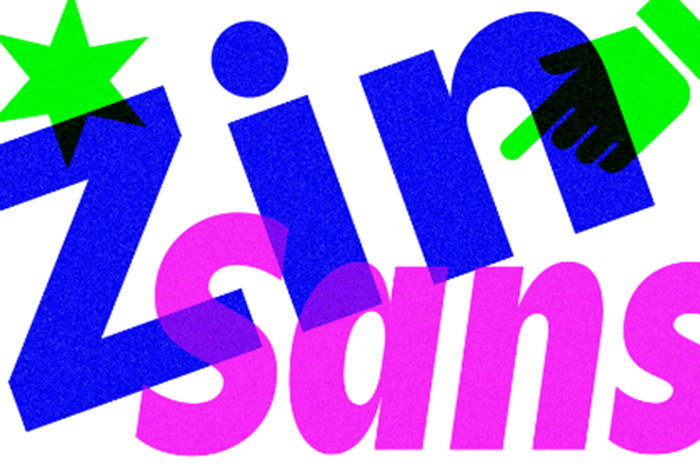
Aproveite uma nova fonte serifless chamada Zin Sans Font Family para suas próximas criações digitais. Introduzida por CarnokyType, a Zin Sans é um tipo de sans-serif projetado para diversas situações na tipografia. Ela destaca-se pela elevada altura do x (x-height), equilibrando uma construção neutra e vertical com formas abertas dinâmicas que têm terminais amplamente abertos. Uma característica notável da fonte é a conexão visual entre os ramos e traços que é mais estreita do que habitualmente encontrada em outros tipos serifless. A Zin Sans vem completa com três proporções de largura (Normal, Condensada e Ampliada), cada uma contendo cinco pesos de tipografia desde o leve até o preto, incluindo itálico correspondente. Todas as fontes incluem minúsculas grandes, caracteres old-style e tabular, ligaturas padrão e alternativas, bem como várias opções tipográficas oferecidas por os recursos OpenType (veja o pdf do espetáculo para mais detalhes). Este é um conjunto de recursos que definitivamente merece ser explorado para enriquecer seu design.